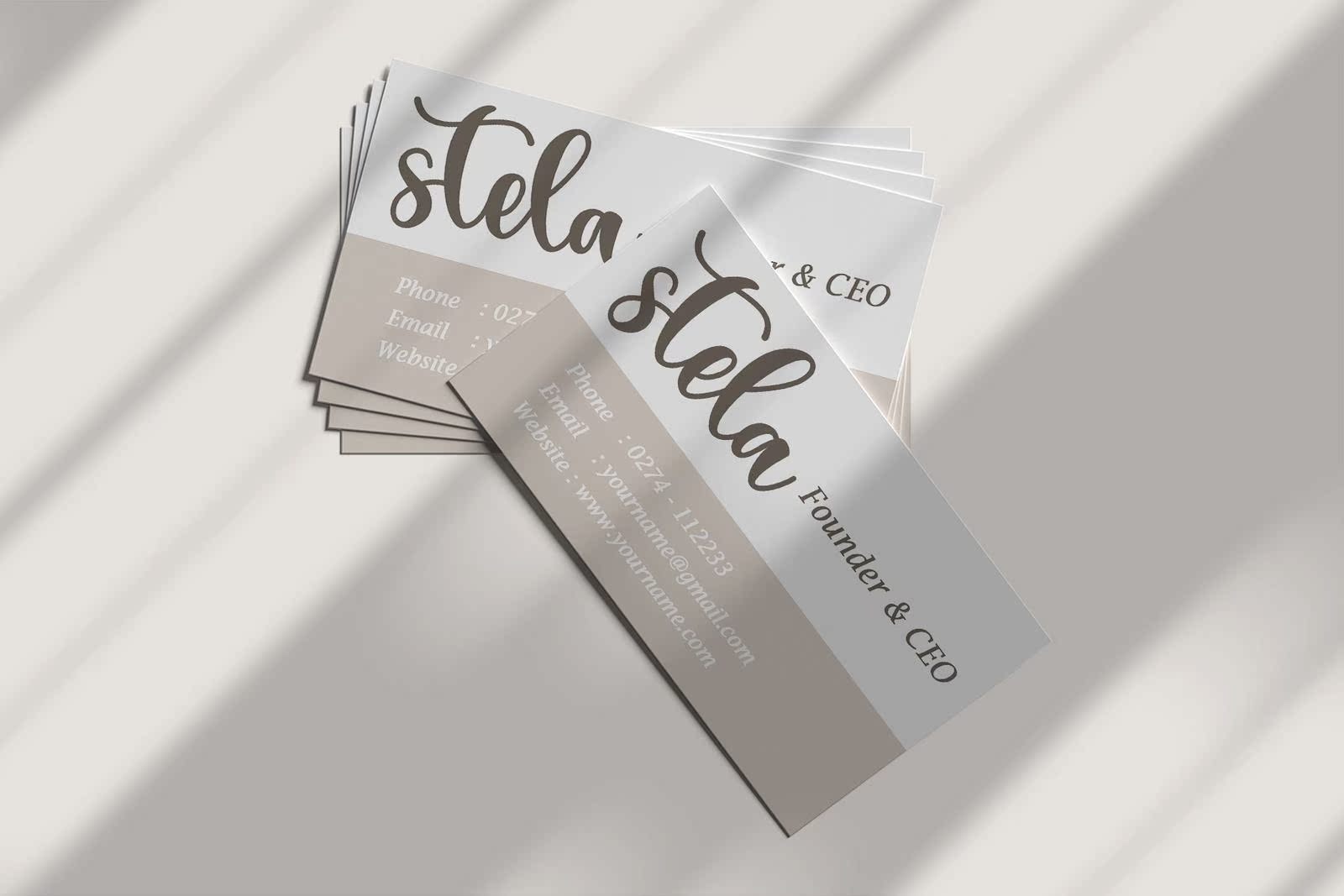
SummerPeachisaadAzzlingScriptFont。此字体笔迹简洁且非常详细。无论是什么样的字体,此字体都将非常适合您的字体库,因为它有可能增强任何创作。此字体的编码意味着您可以访问所有的字形和SWASE!SummerPeachisaadAzzlingScriptFont。此字体笔迹简洁且非常详细。无论是什么样的字体,此字体都将非常适合您的字体库,因为它有可能增强任何创作。此字体的编码意味着您可以访问所有的字形和SWASE!